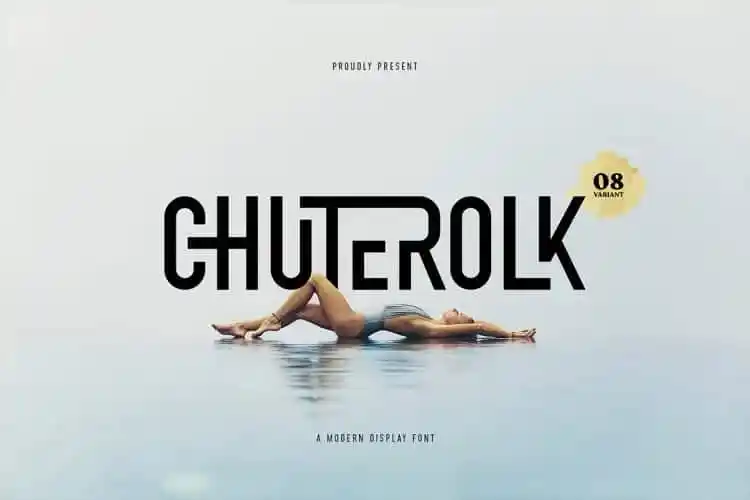
A fonte CHUTEROLK Sans Serif é uma escolha perfeita para qualquer projeto moderno que busca estilizar sua identidade visual de maneira futurista e sofisticada. Desenvolvida pelo Namara Creative Studio, esta fonte oferece um equilíbrio entre pontas firmes e curvas fluidas, o que a torna uma escolha versátil para diversos fins, especialmente adequada para headlines. Sujeitável a 8 variantes diferentes, inclui Light, Light Italic, Regular, Italic, Rounded, Shadow, Distort e outlines, assim como alternativas de caracteres, ligaduras e suporte multilíngue. A CHUTEROLK Sans Serif é ideal para designers que desejam dar um toque único aos seus projetos, seja criando headlines impressionantes ou textos mais complexos. Com sua rica variedade de opções, ela certamente atenderá às suas necessidades estéticas e funcionais. Se você está procurando uma fonte que combine modernidade com simplicidade, a CHUTEROLK Sans Serif é sem dúvida o item indispensável para seu portfólio.